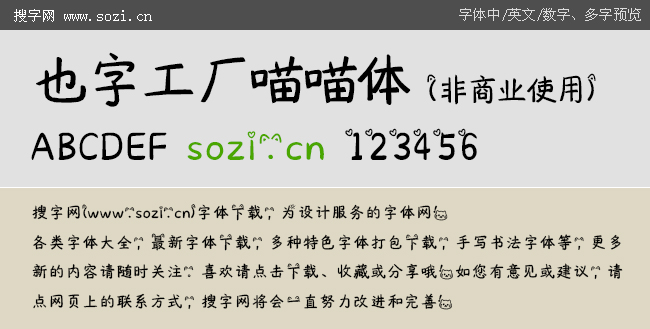
也字工廠喵喵體
搜字網(wǎng)給大家提供一款也字工廠喵喵體(非商業(yè)使用)中文字體下載,也字工廠喵喵體是一款卡通字體,字體是可愛的書寫風(fēng)格,非?蓯塾腥,具有很好的視覺效果。適合應(yīng)用于兒童繪本、兒童海報(bào)、網(wǎng)頁(yè)設(shè)計(jì)等應(yīng)用(此字體為個(gè)人非商用版,商用可以聯(lián)系:官方網(wǎng)址:https://yefont.com/home,聯(lián)系方式:13798980448)。